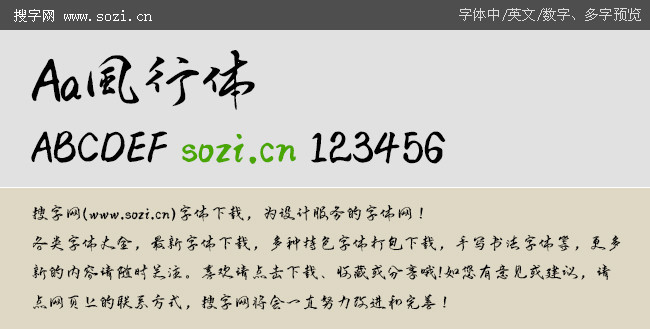
Aa風(fēng)行體字體
搜字網(wǎng)給大家提供一Aa風(fēng)行體字體中文書(shū)法字體下載,這是一款非常漂亮的硬筆書(shū)法字體,書(shū)寫(xiě)流暢,瀟灑大方,適合海報(bào)設(shè)計(jì)、畫(huà)冊(cè)設(shè)計(jì),廣告設(shè)計(jì)等應(yīng)用(此字體為個(gè)人非商用版,如需商用請(qǐng)聯(lián)系作者購(gòu)買(mǎi)版權(quán))。